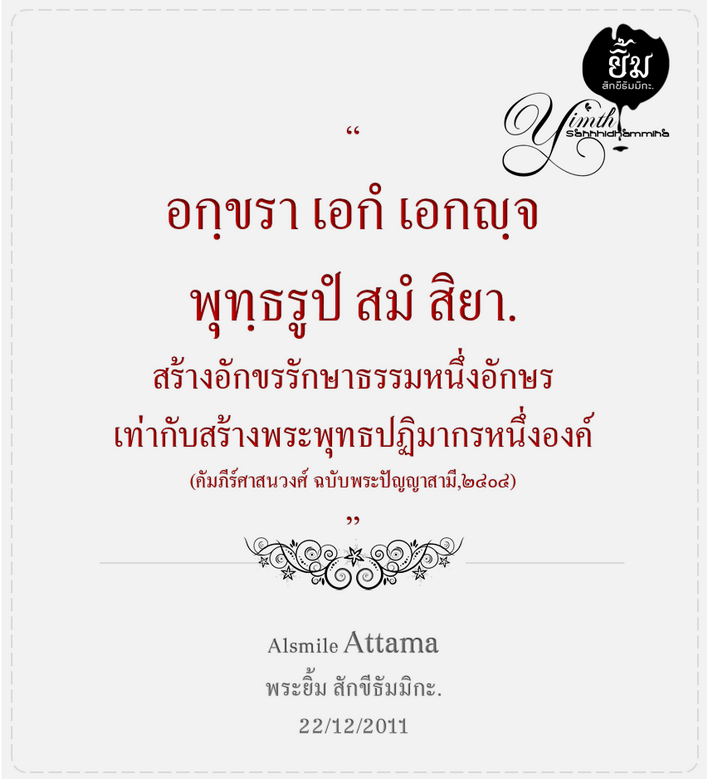
คิดจะทำฟอนต์ให้เหมาะกับเทศกาล
มีไอเดียจะทำฟอนต์แต่ละเทศกาล แต่ตอนนี้ยังไม่ทันได้เริ่มเลย
คิดจะทำฟอนต์ Christmas แต่ยังไม่ลงมือทำ พอ ๆ อยู่ในสมองสองซีก
เดี๋ยวทำเสร็จจะเอามาลง แต่อาจไม่ทันได้ใช้ในเทศกาลนี้แน่เลย
ฏ-ฎ เปรี้ยวมากครับ เจ๋ง
สวยครับ กรี๊ดดดดด
ยังคงมาได้อีกเรื่อยๆ จริงๆ เลยหลวงพี่ กรี๊ดดดดด กรี๊ดดดดด
สวยสะเทือนใจ กรี๊ดดดดด
ยังไม่ได้ปรับช่องไฟน่ะ แต่เอามาลงก่อน  อืมมมมห์
ชื่อฟอนต์นี้คิดไม่ทัน มองเห็นอะไรใส่มันยังงั้นไปก่อน
ทำให้มันเสร็จ ๆ ไป แล้วค่อยปรับ...อึม.
ฮือๆ~ เบ่งฟอนต์ใหม่รายวันจริงๆ
แล้วเมื่อไหร่จะได้ใช้ของเก่าล่ะครับหลวงเพ่  ฮ่าๆ ฮือๆ
รอมานาน หวังมานาน ในที่สุด เราก็บันดาลให้มันบังเกิดขึ้นจงได้
โอย โอย...ชอบใจ...